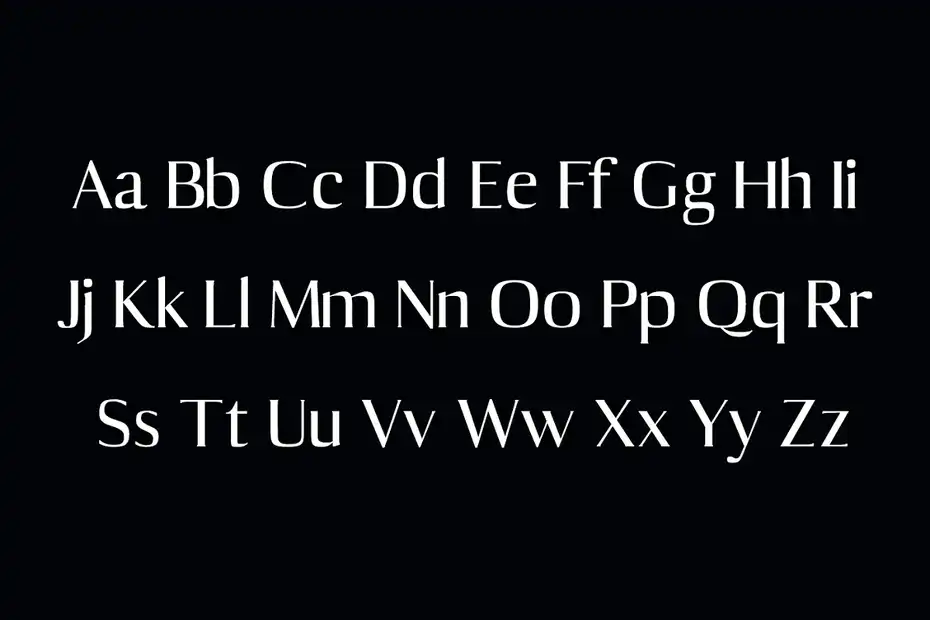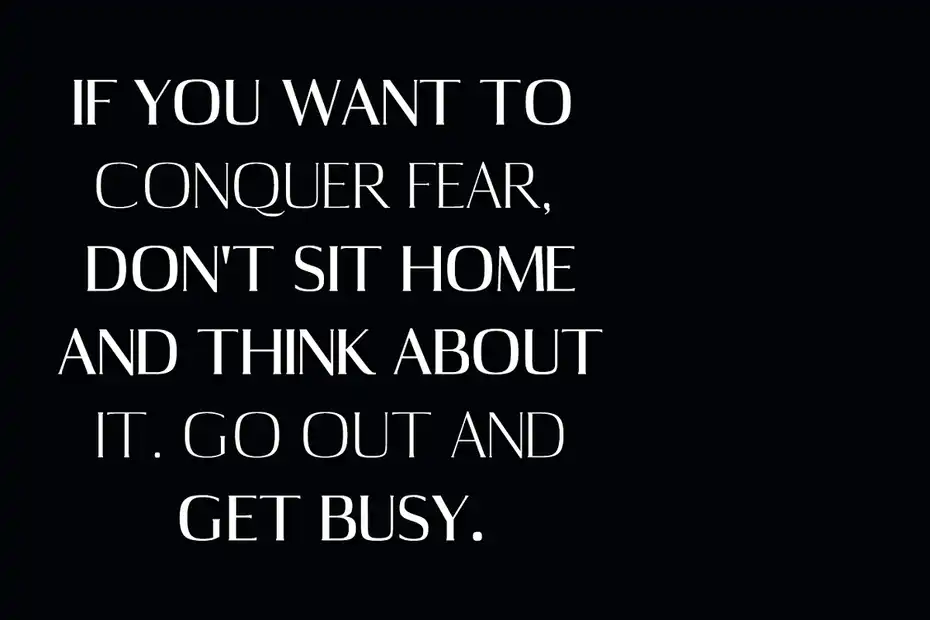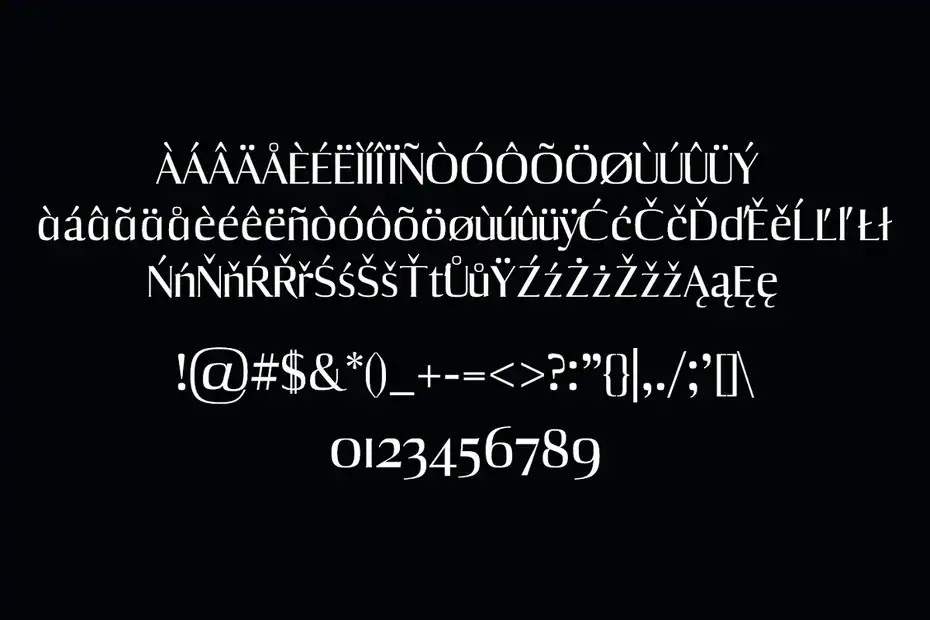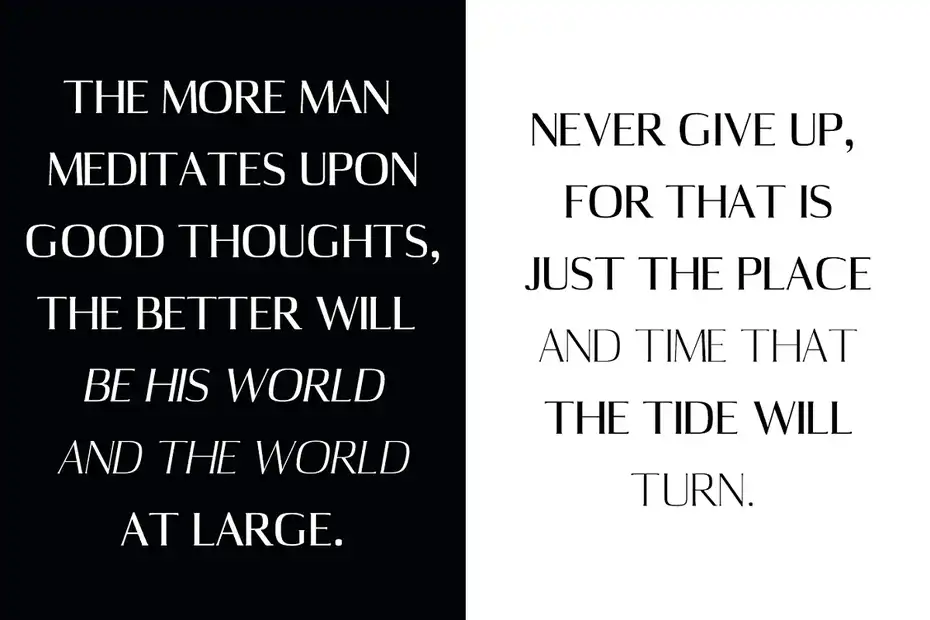
دانلود فونت انگلیسی مدرن Abril Serif Font Family Pack
فونت انگلیسی مدرن Abril Serif Font Family Pack : این مجموعه شامل یک فونت انگلیسی مدرن است که برای لوگو، سرفصل‌، بنر و غیره مناسب میباشد.
فونت انگلیسی مدرن Abril Serif Font Family Pack - 1
فونت انگلیسی مدرن Abril Serif Font Family Pack - 3
فونت انگلیسی مدرن Abril Serif Font Family Pack - 5
فونت انگلیسی مدرن Abril Serif Font Family Pack - 7